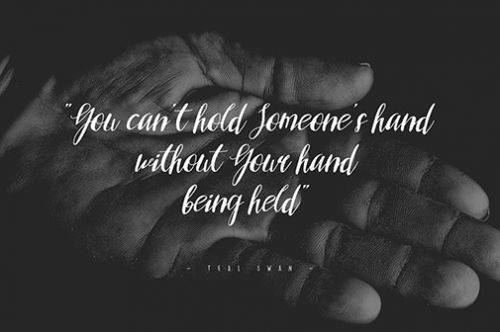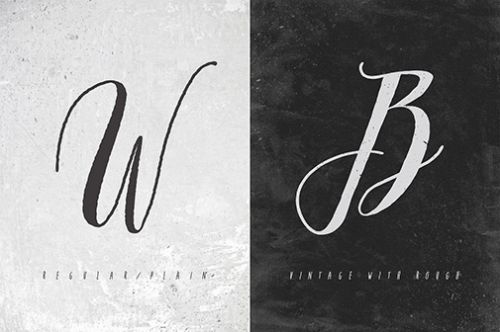
Arkana
Arkana Script Rough 是一款充满艺术张力的英文手写风字体(Handwriting)。其修长的字型结构配合居中的字体重心,中宫宽博的设计让字符兼具优雅与舒展感。粗重而均匀的线条搭配圆润的笔画端头,通过自然的连笔设计与精致装饰元素,营造出流畅而富有韵律的手写质感。 Arkana Script Rough 在保留手写字体自然韵味的同时,通过刻意强化的笔触力度与连贯的字符连接,赋予设计作品强烈的视觉冲击力。无论是贺卡设计、品牌标识还是社交媒体视觉创作,其独特的装饰性连笔与饱满的字形结构都能为作品注入温暖而富有个性的艺术气息。 作为支持免费商用授权的英文字体,Arkana Script Rough 兼顾设计品质与使用成本优势,是英文手写风格设计项目的理想选择。